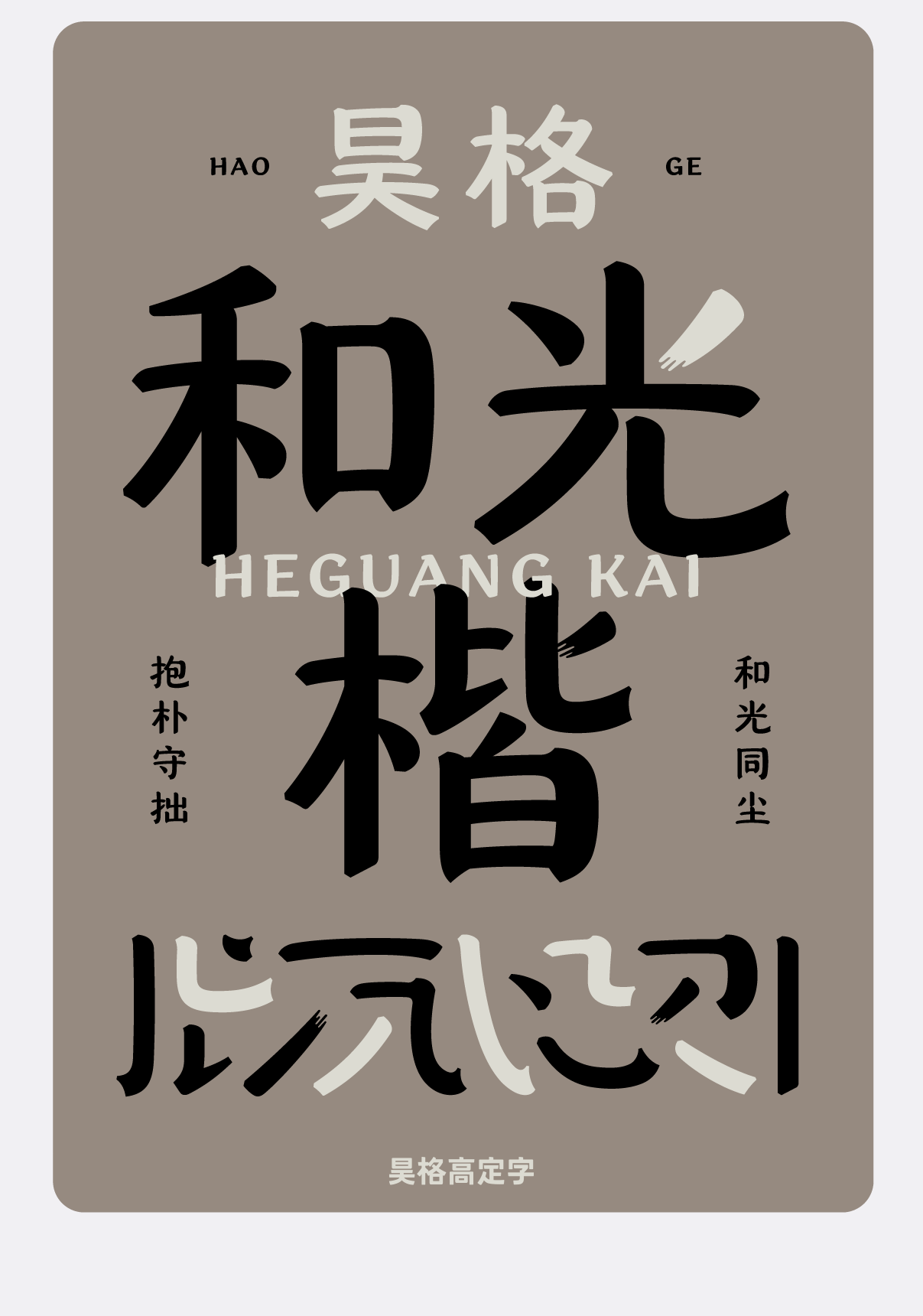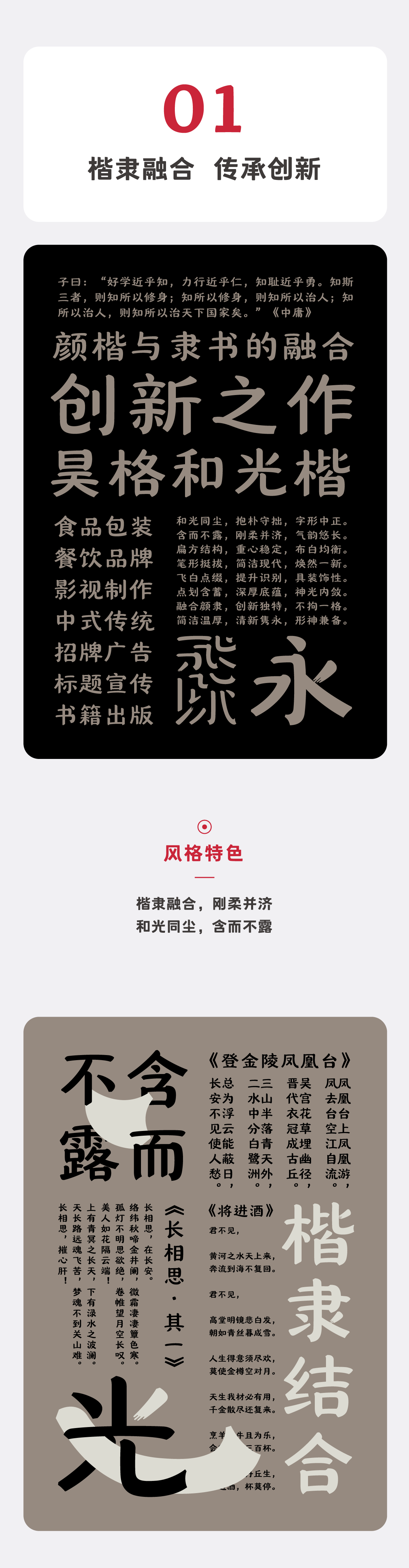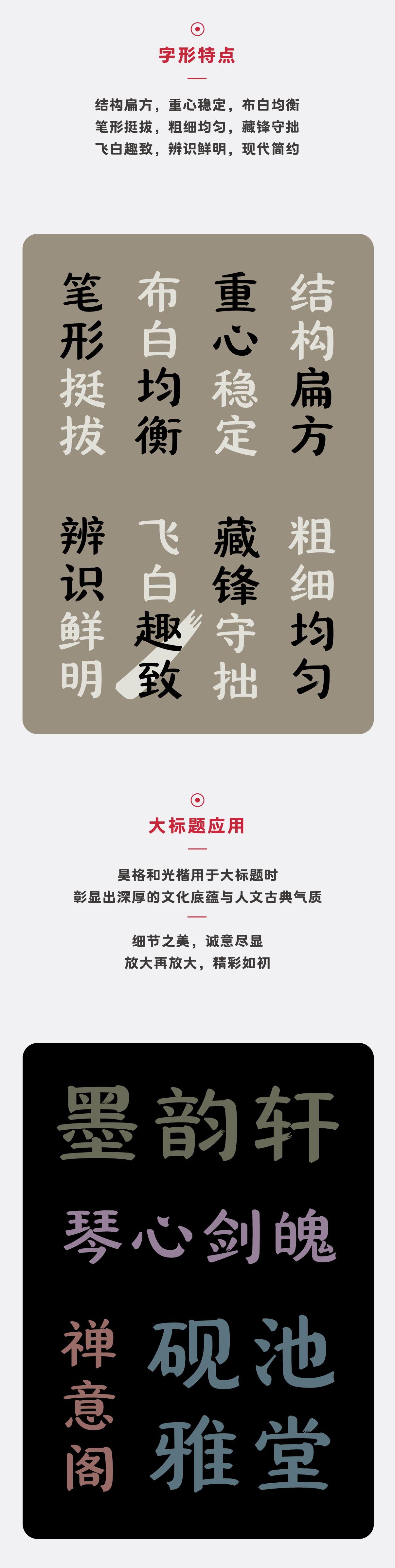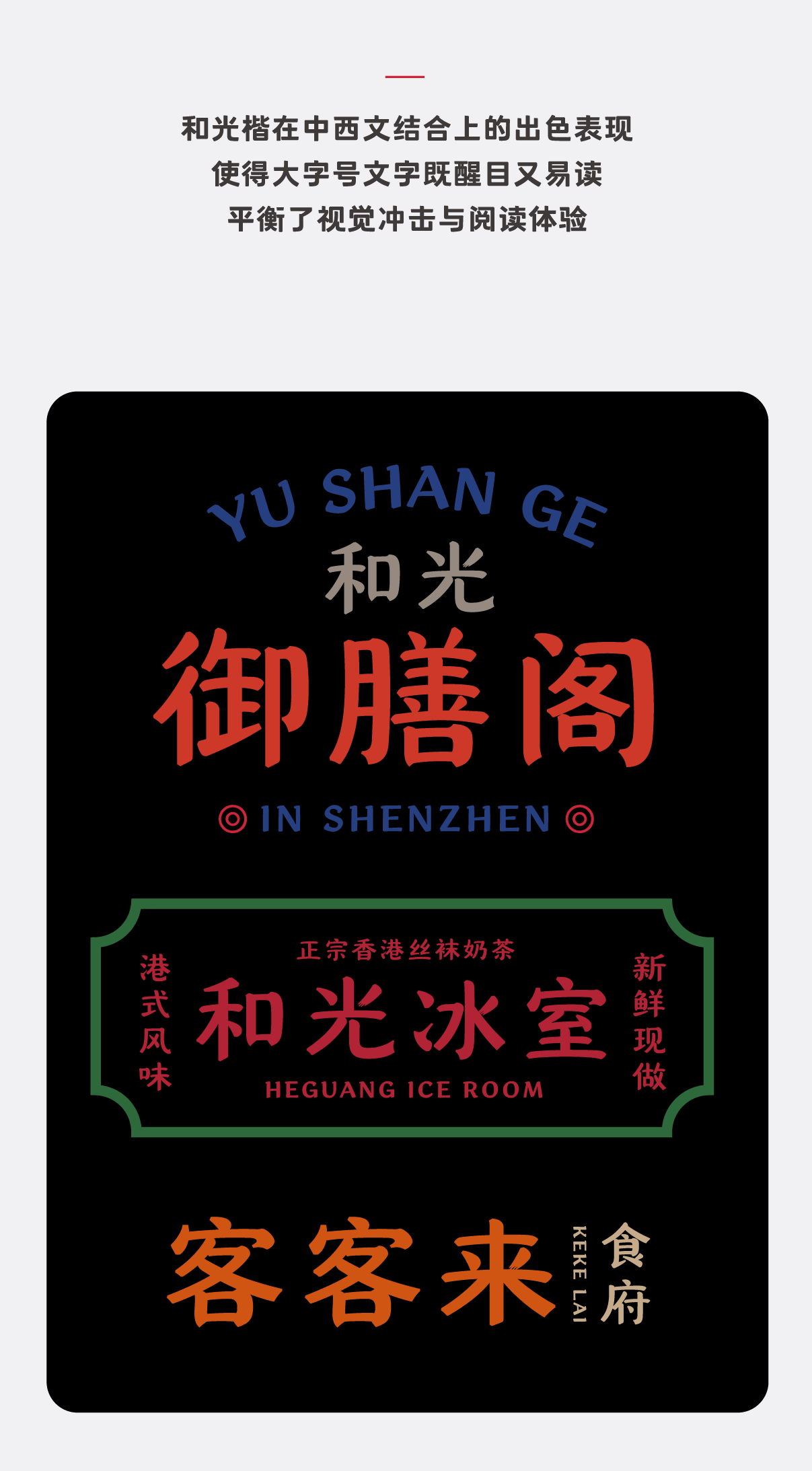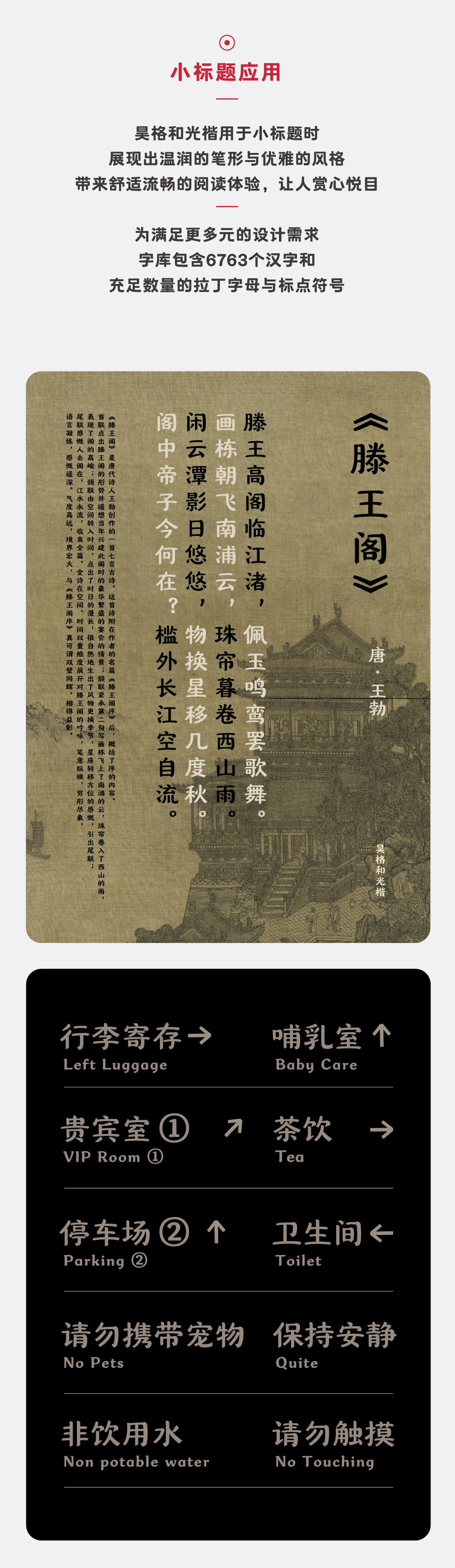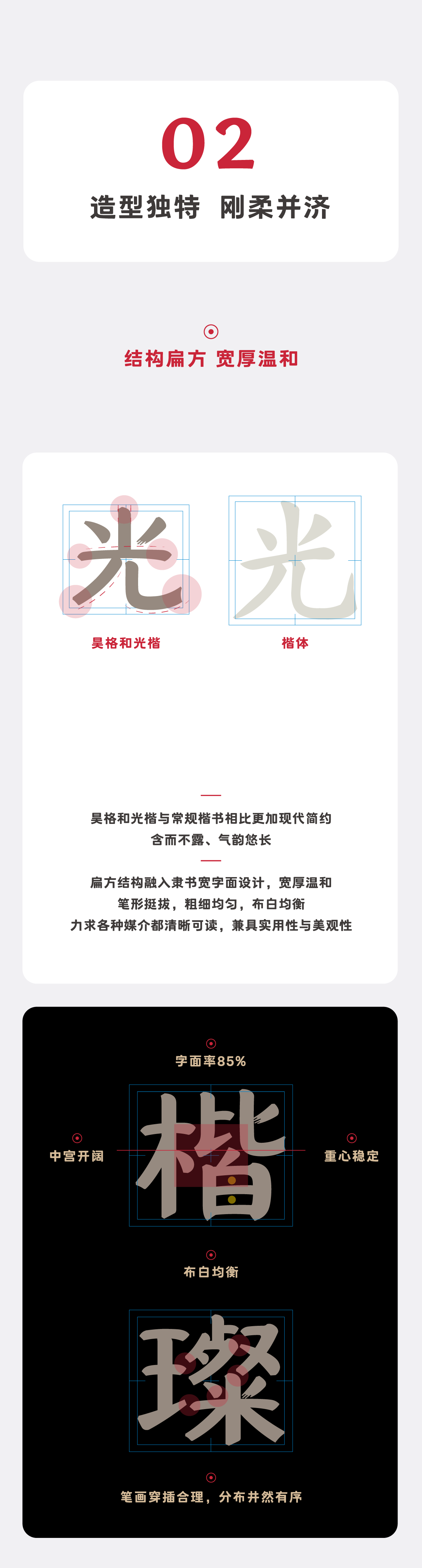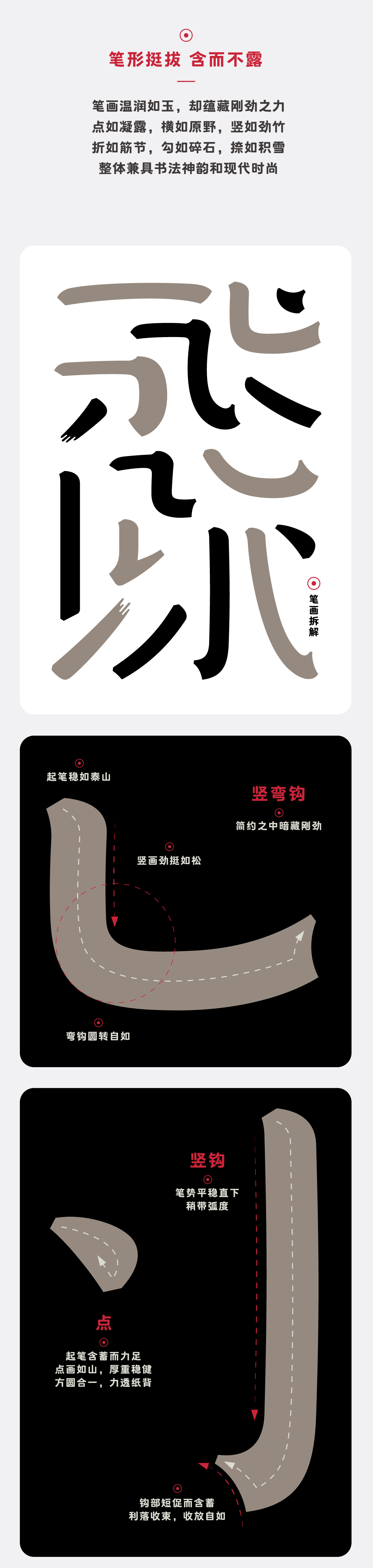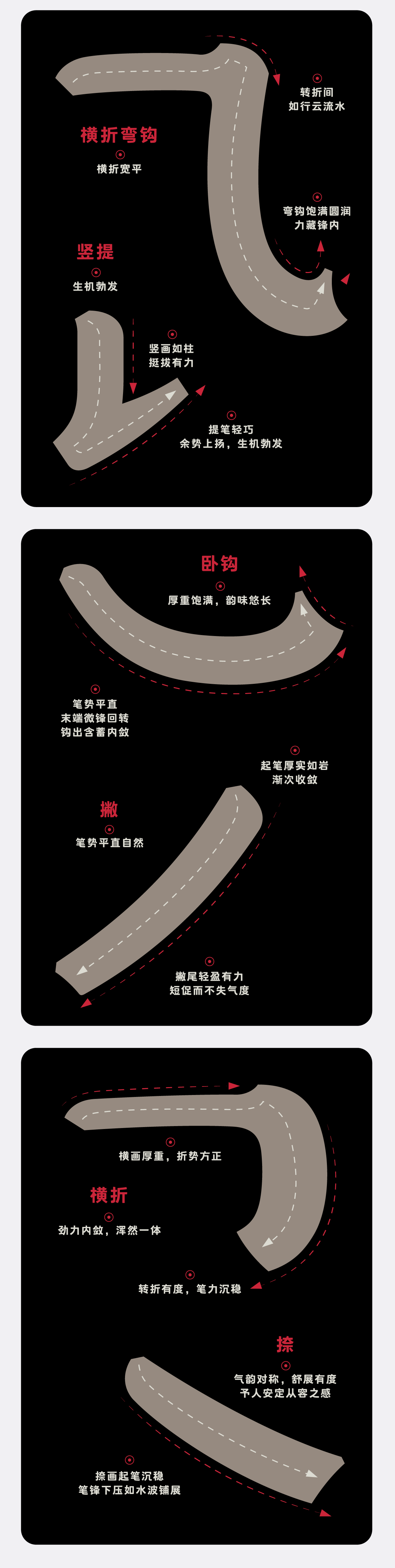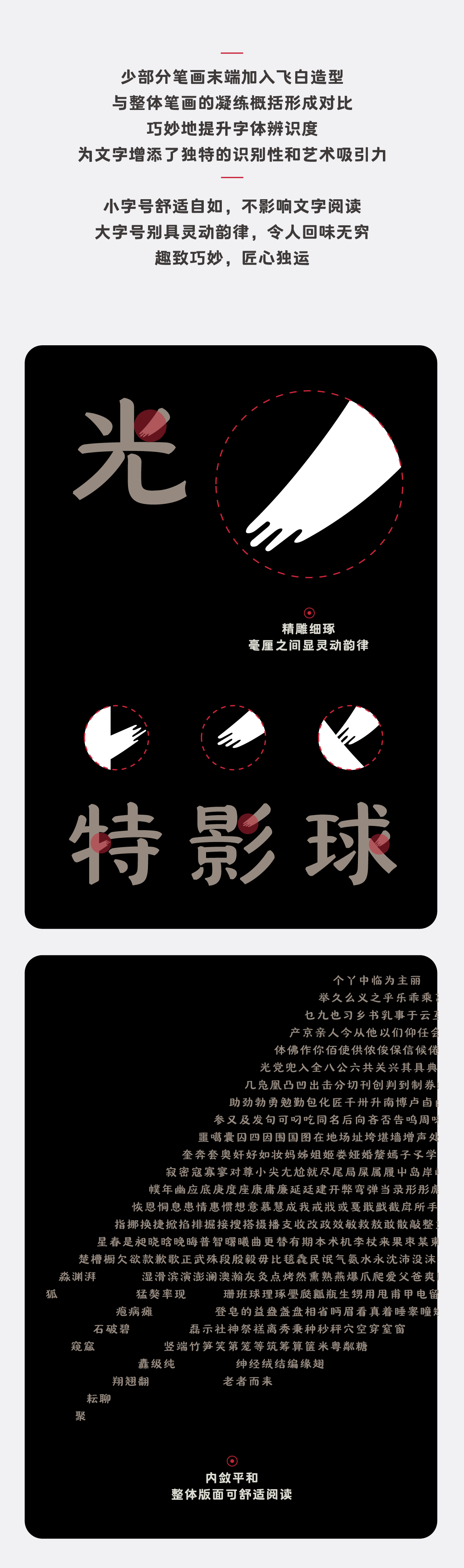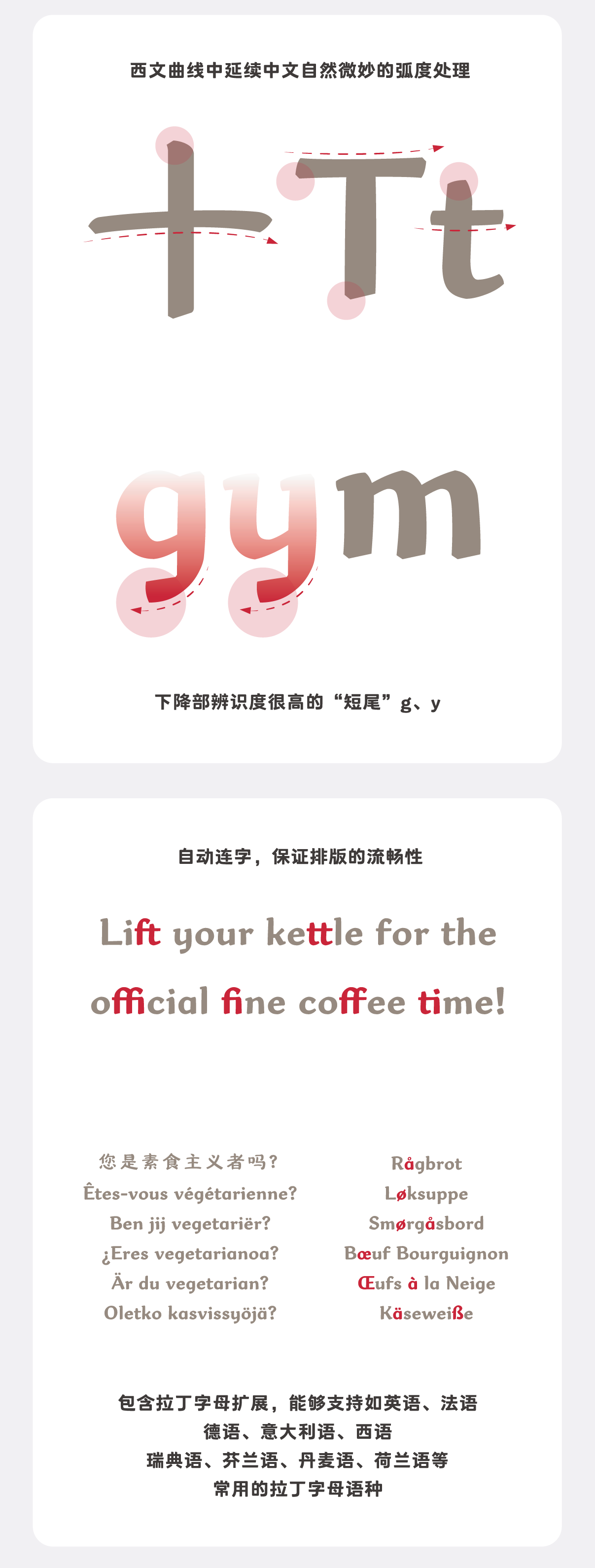
昊格和光楷
昊格和光楷,和光同尘,抱朴守拙,昊格和光楷是一款兼具颜楷与隶书特征的创新字体。结构上,字面扁方、重心适中、布白均衡、结体稳定;笔形上,挺拔舒展,运笔的起承转合在颜楷基础上进行大胆概括,使其简洁现代、焕然一新;细节上,部分笔画大胆使用飞白,增强辨识度和装饰性。昊格和光楷整体含而不露、刚柔并济,适合众多使用场景。字体覆盖 GB/T 2312-1980 编码字符集中的全部6763个汉字。除基础拉丁字母外,覆盖欧洲、非洲、亚洲、大洋洲、南美洲各种语言所需的字符共211个,可支持 90 余种语言,包括英语、法语、德语、西班牙语、芬兰语。支持阿拉伯数字、大小写罗马数字,以及其他 4 种样式的数字序号①⑵⒊㈣。包含标点和其他各类符号共 200 余个。商业用途
昊格和光楷字体介绍